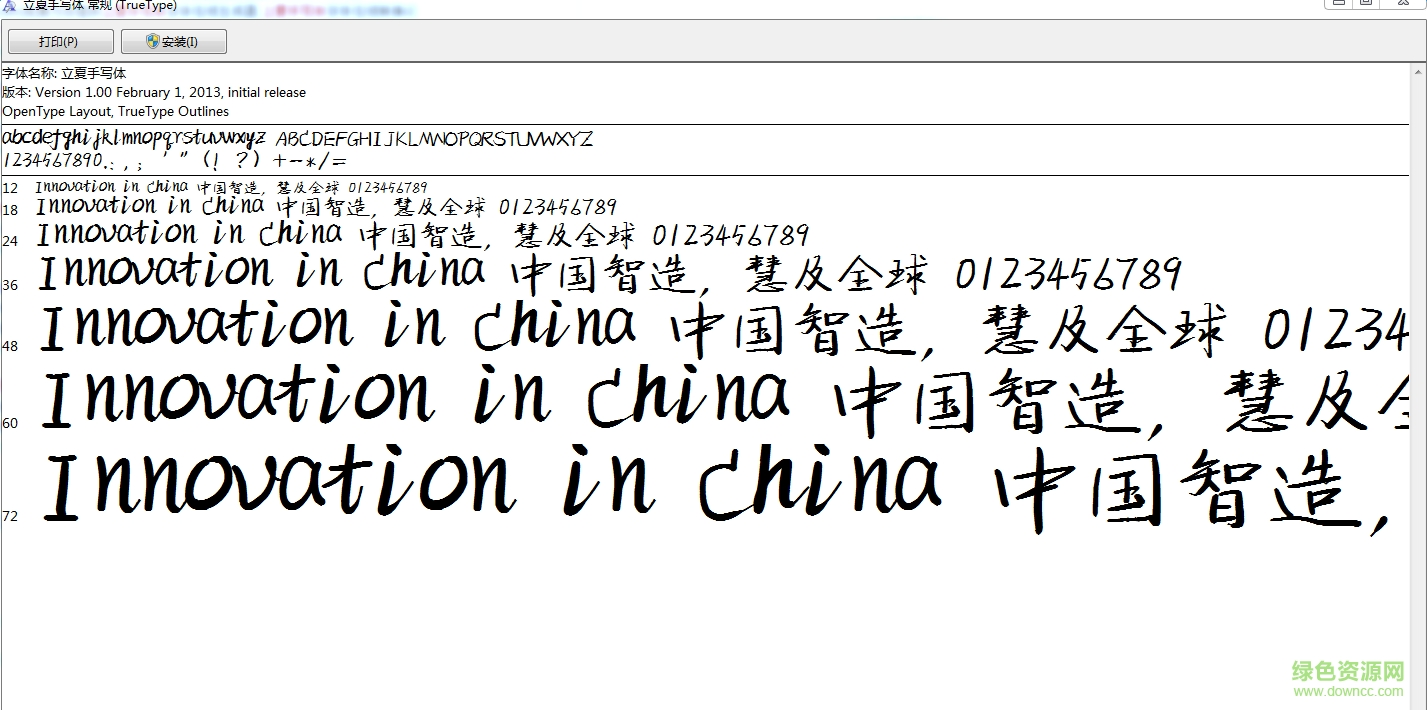
立夏手寫體ttf字體是一款極具個(gè)性的手寫字體,字形灑脫,線條潦草,可用于藝術(shù)設(shè)計(jì)或創(chuàng)意設(shè)計(jì)領(lǐng)域,歡迎大家在綠色資源網(wǎng)下載!
立夏手寫體是一款設(shè)計(jì)方面的中文簡(jiǎn)體漢字,字體全部為手寫方式,飄逸大方,可應(yīng)用于廣告計(jì)、藝術(shù)創(chuàng)作、平面設(shè)計(jì)、印刷包裝、個(gè)性簽名等領(lǐng)域,喜歡的朋友可免費(fèi)下載收藏。